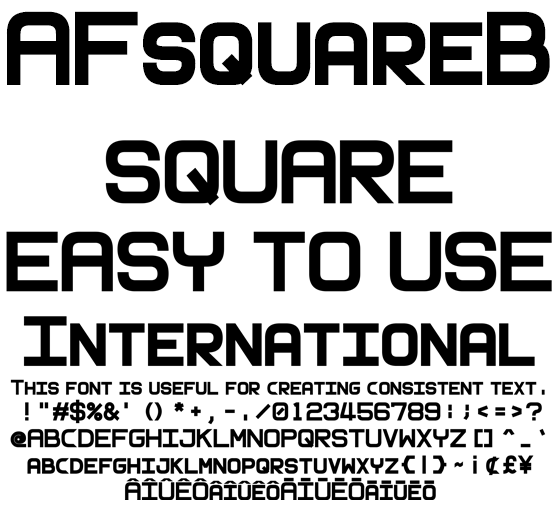
四角ぽいボディな欧文 AFsquareB
AFsquareB
個々字形の特徴に左右されず縦横が同じサイズで作られた等幅欧文フォントです。統一され縦横にでこぼこがない流れるようなデザインはモダンな表現に最適です。太字のボールドで強調されたワードは、動画のエンドロール、テロップ、液晶表示器、操作パネル、メニューなど強調かつ幅を統一させたい場所にご利用ください。